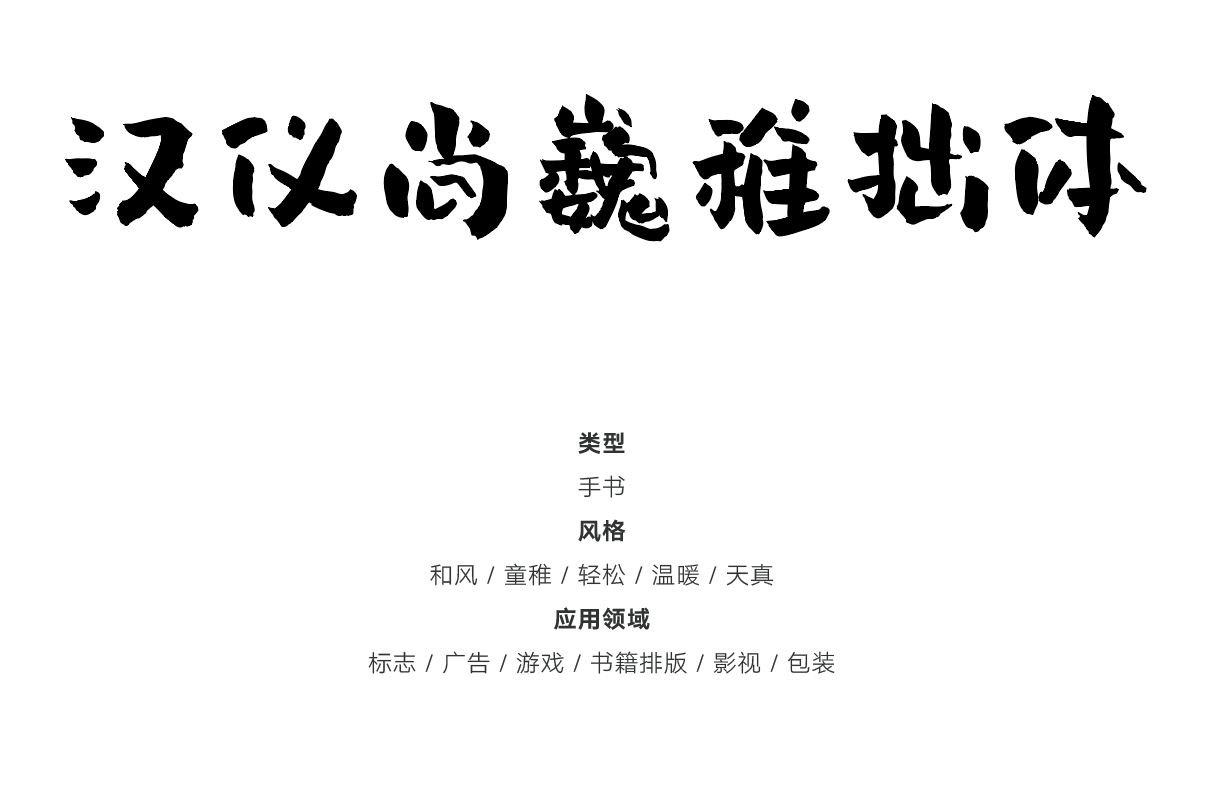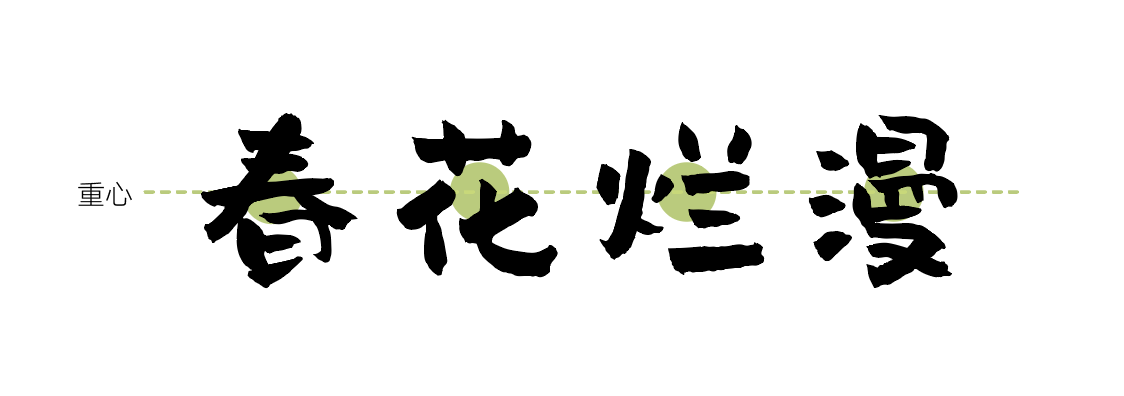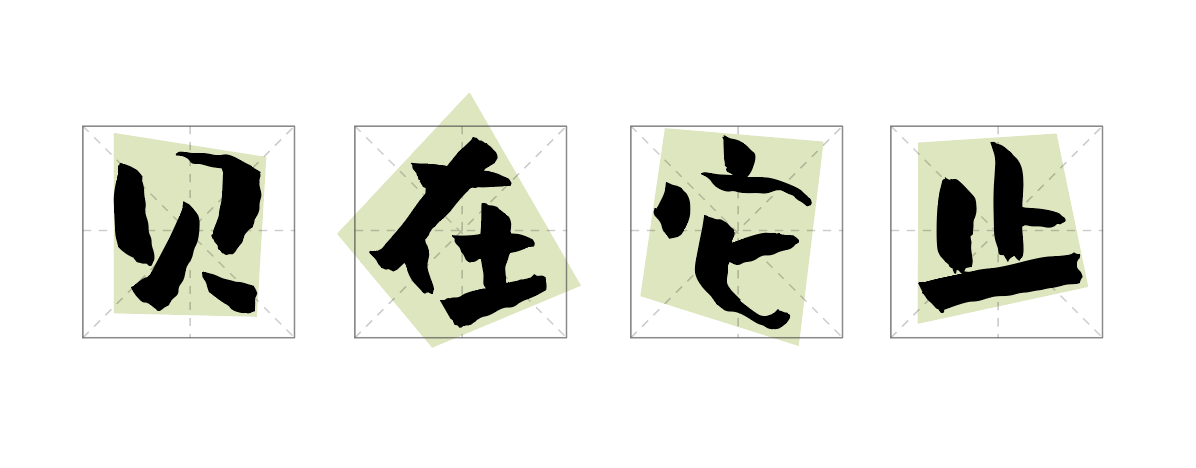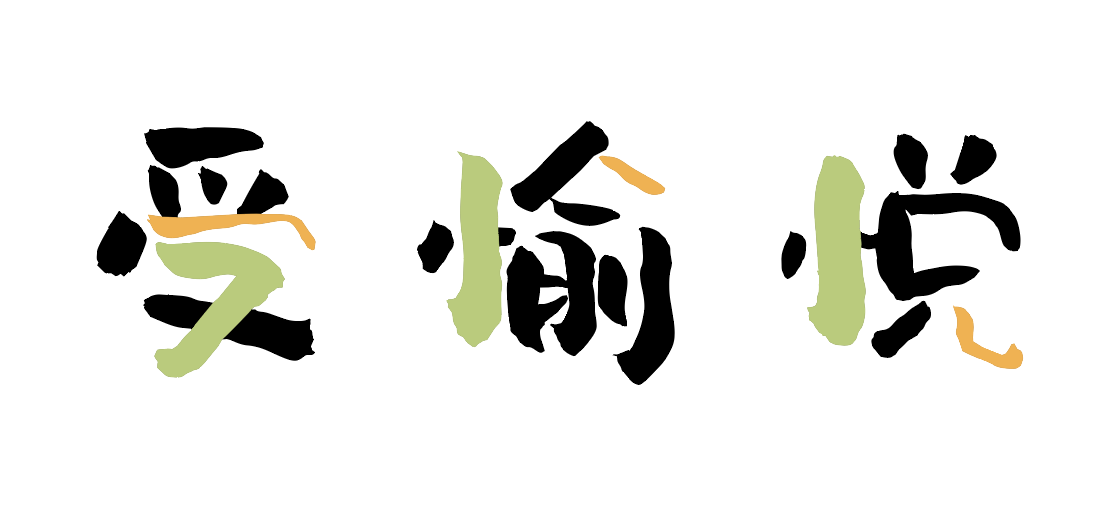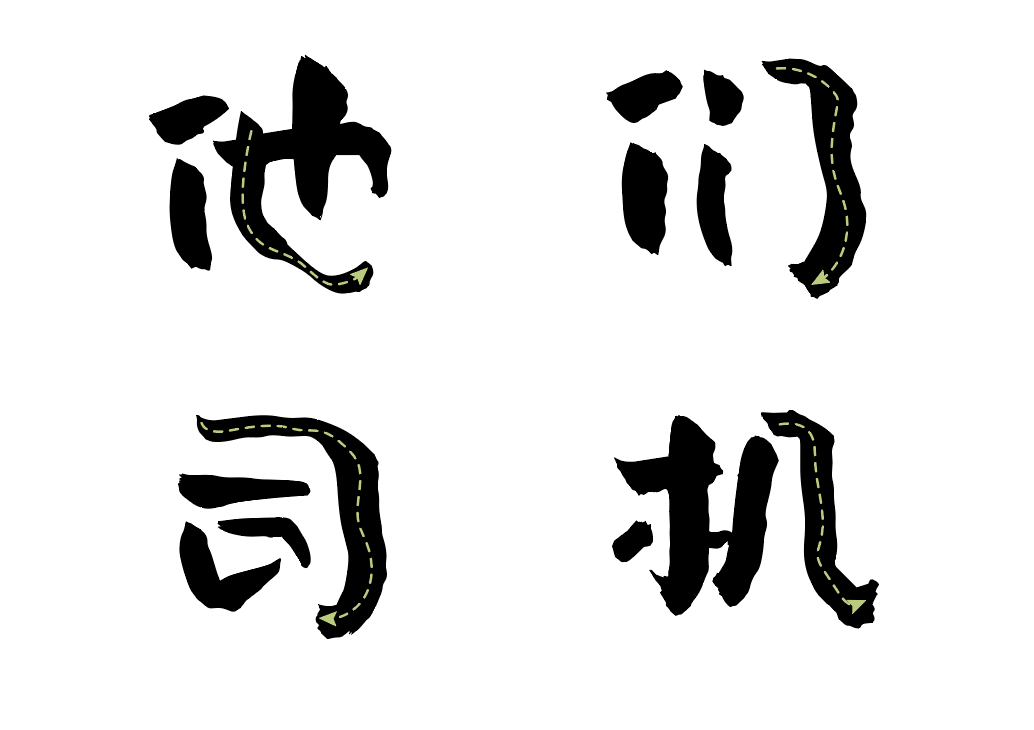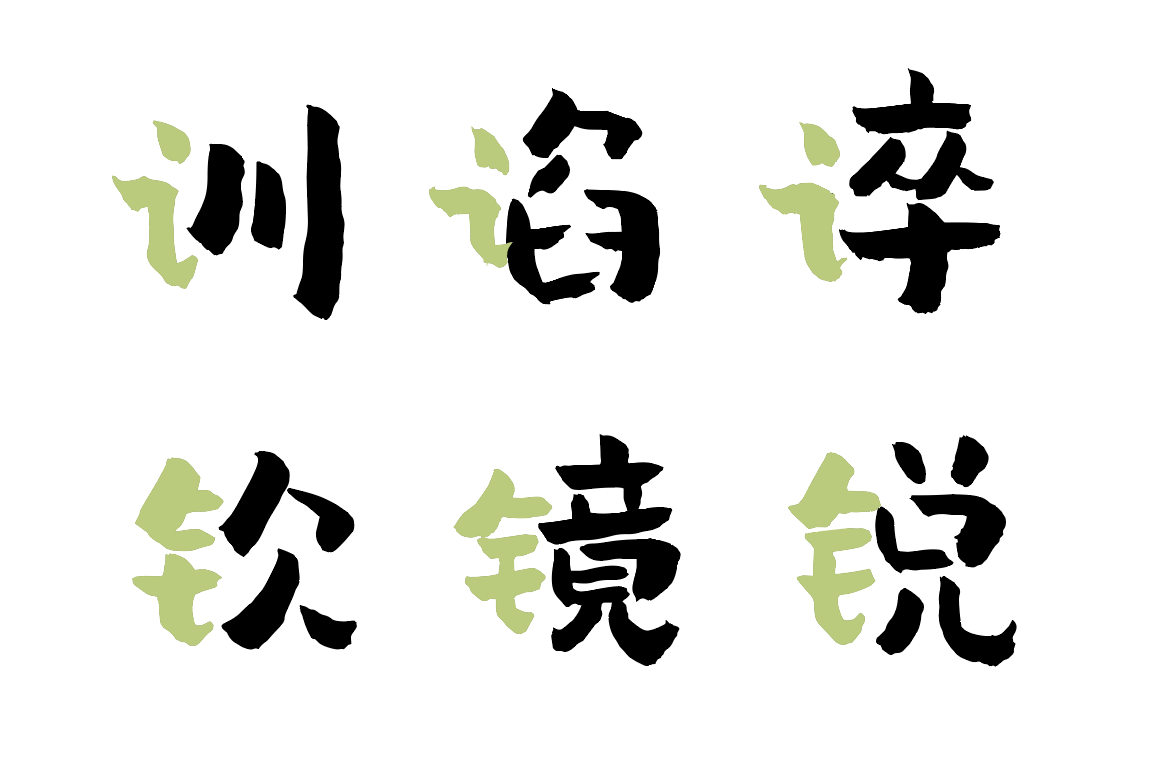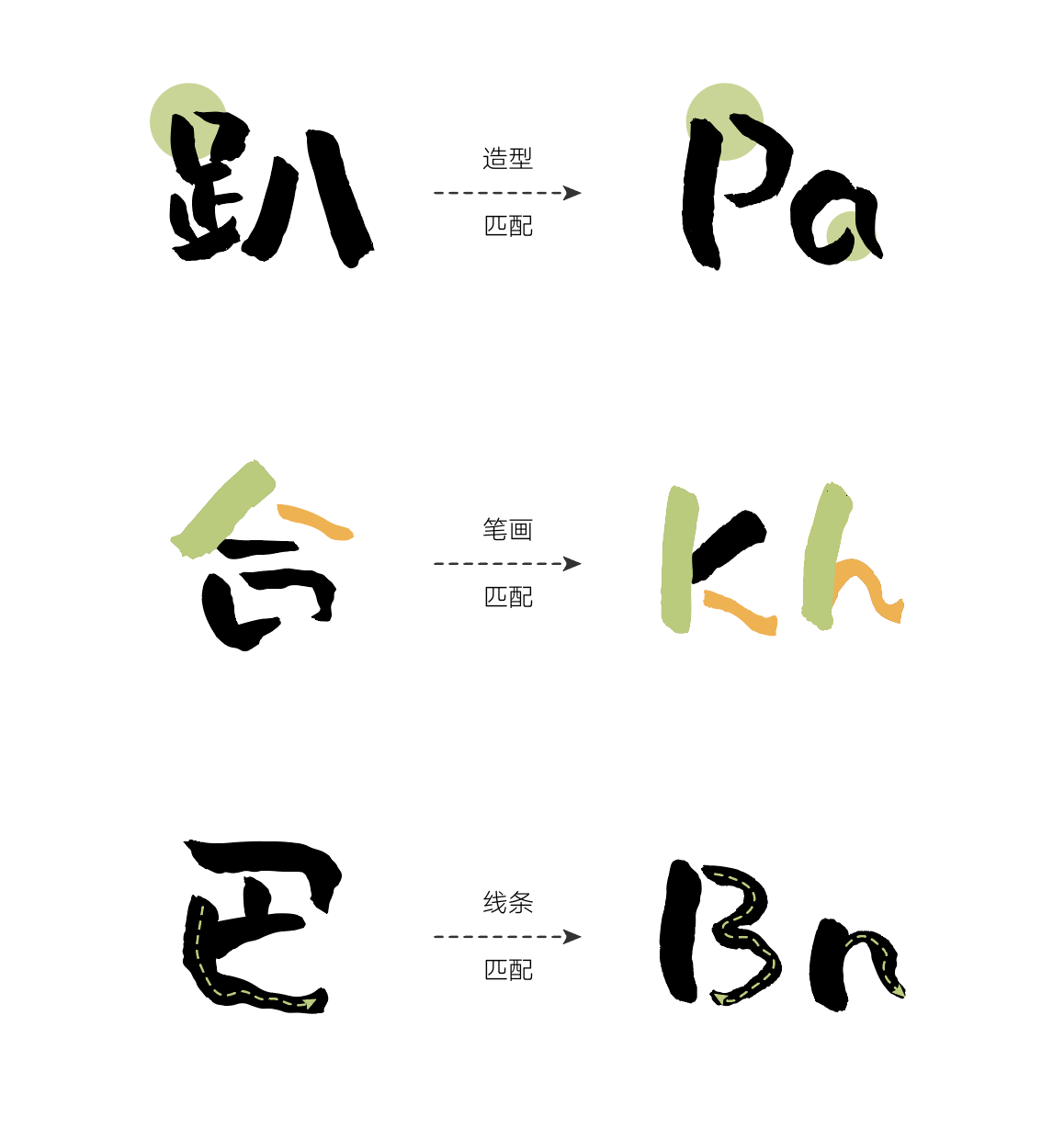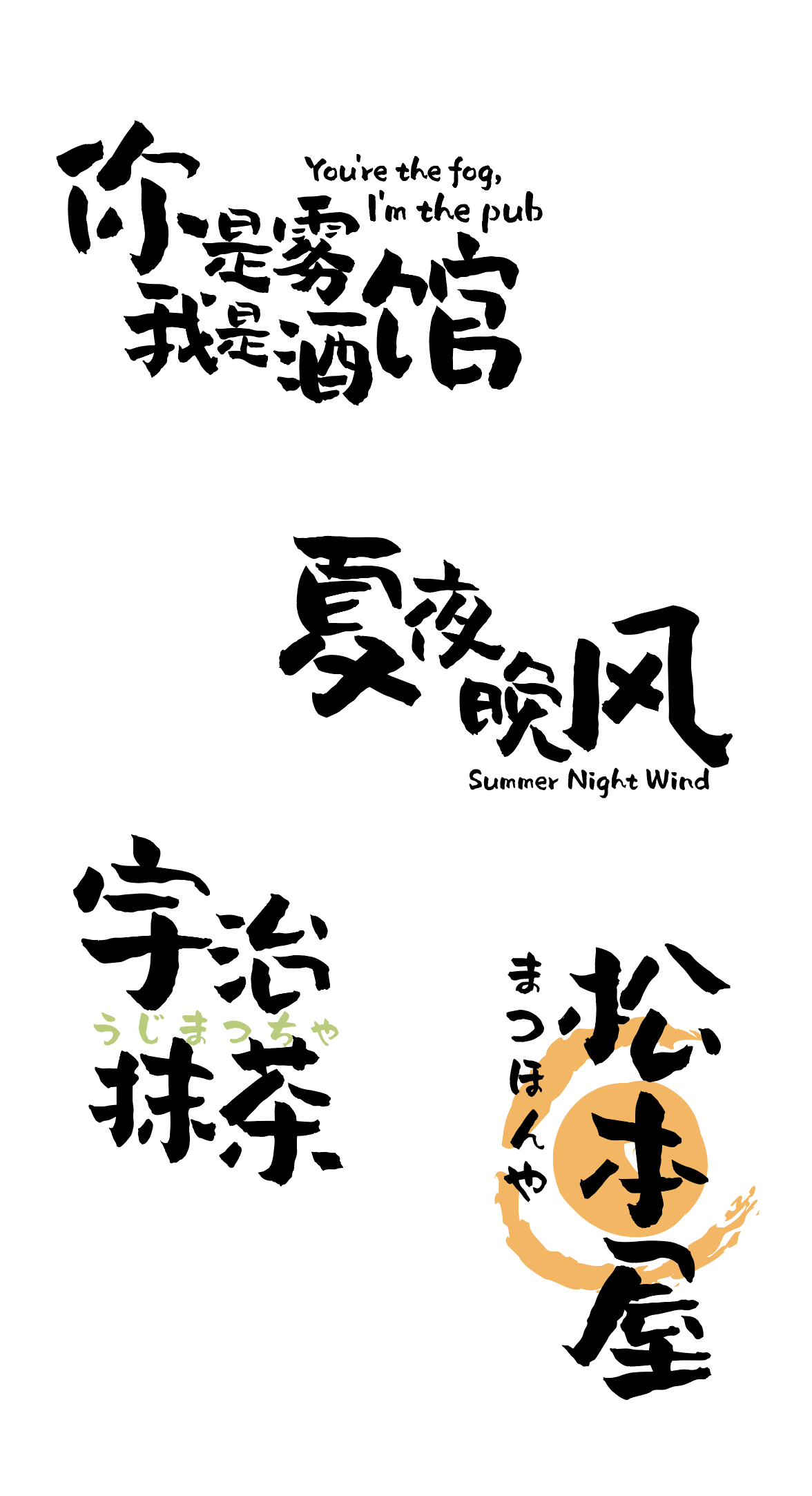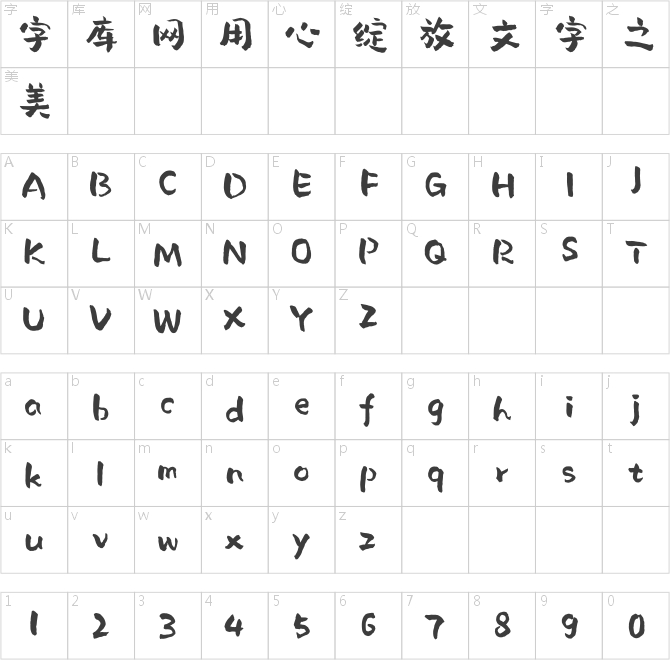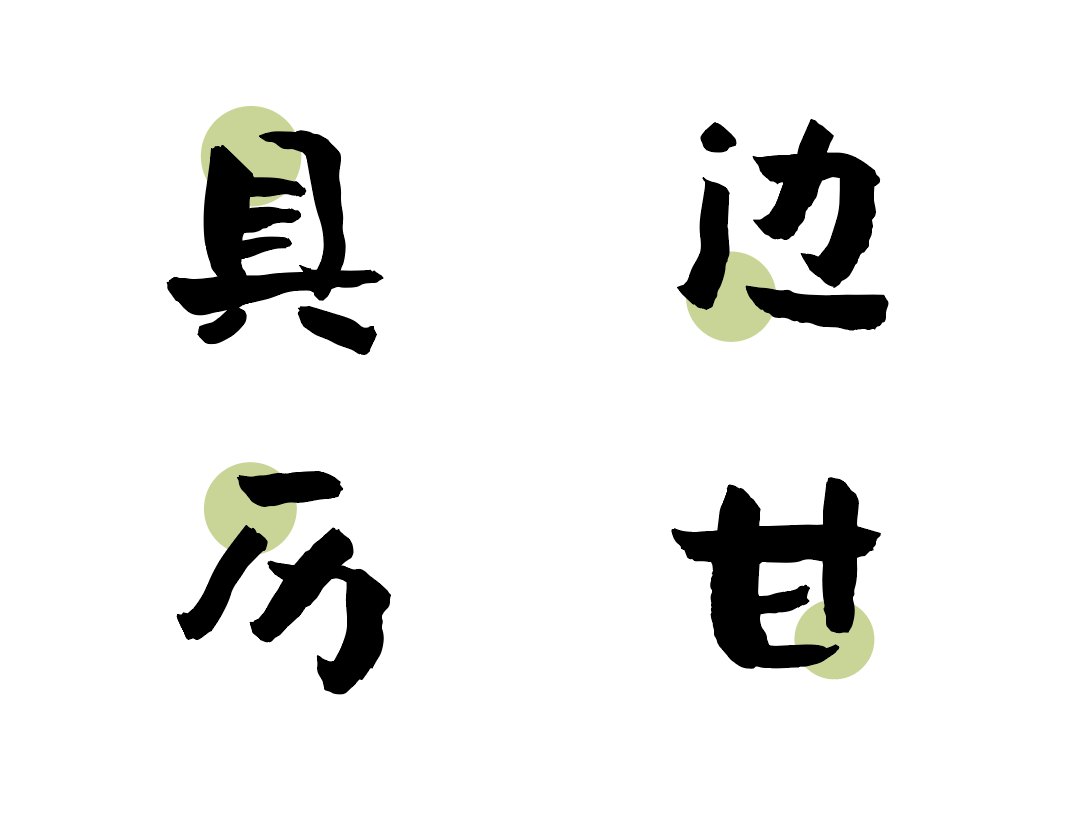
漢儀尚巍稚拙體
漢儀尚巍稚拙體 | 天真稚拙
漢儀尚巍稚拙體為90后新銳字體設(shè)計(jì)師尚巍所做的一款有著日和風(fēng)格的手書字體。作者在書寫時(shí)處于非常放松的狀態(tài),使得字體給人一種輕松緩和的視覺效果,非常具有親和力。
漢儀尚巍稚拙體 | 字形多變
漢儀尚巍稚拙體的字形布局考究、張弛有度。筆畫排布看似隨意卻又能夠在視覺上保持統(tǒng)一,給人帶來溫暖的松弛感和親切感。
漢儀尚巍稚拙體的結(jié)構(gòu)多變,部分字形打破常規(guī)。雖然看似放縱隨意,但其實(shí)每個(gè)字都被限制在字框中。
漢儀尚巍稚拙體 | 筆畫童稚
漢儀尚巍稚拙體筆畫的粗細(xì)變化十分明顯,作者用筆時(shí)而堅(jiān)實(shí)有力,時(shí)而頑皮隨性。
漢儀尚巍稚拙體的書寫手法質(zhì)樸拙嫩、直率自然,筆畫提按過渡明顯,線條變化自由生動(dòng),看似如兒童書寫般彎曲隨意卻又帶一股力度和韌勁。
漢儀尚巍稚拙體在筆畫銜接處的留白讓人聯(lián)想到兒童在寫字時(shí)的笨拙可愛,生命力表現(xiàn)十足。
漢儀尚巍稚拙體保留手寫的獨(dú)創(chuàng)性,減少機(jī)械復(fù)制,使相同的偏旁出現(xiàn)不同的手寫效果。
中西文匹配
漢儀尚巍稚拙體的西文充分吸收了中文筆畫造型和線條的特點(diǎn),形成了帶有樸拙韻味、風(fēng)格童稚天真的字母。中西文搭配使用時(shí)和諧統(tǒng)一。